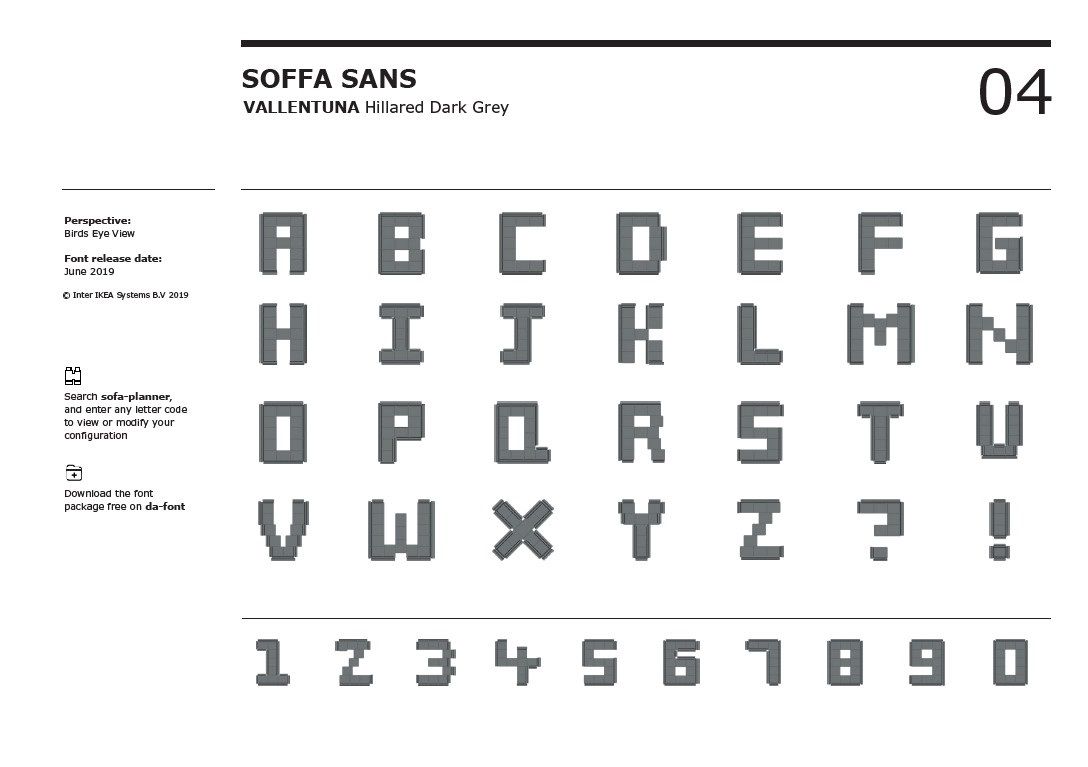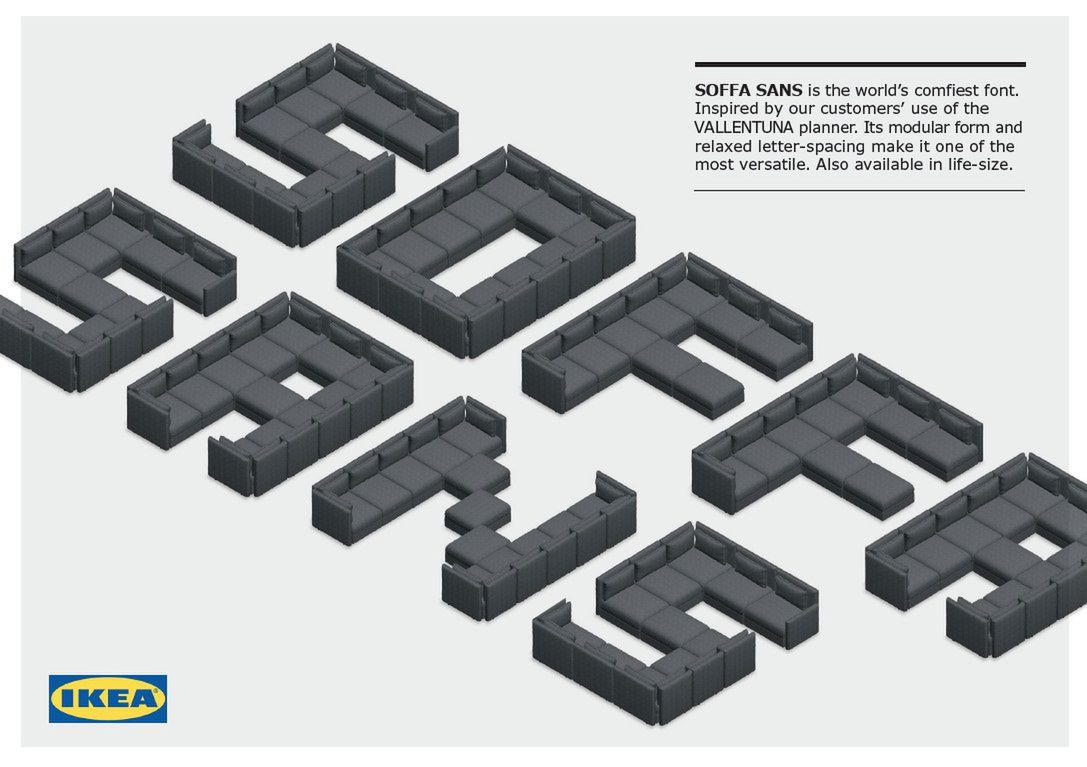
IKEA Soffa Sans. Kto by pomyślał, że sofa może zainspirować do stworzenia czcionki
Nie śpią, bo przeglądają internetowe memy. Tak, parafrazując klasyk polskiego dziennikarstwa, można podsumować najnowszy ruch PR-owców sieci IKEA. Wychodząc naprzeciw internetowym śmieszkom, szwedzki producent mebli udostępnia czcionkę o wymownej nazwie Soffa Sans.
Soffa Sans to czcionka, która jest inspirowana elementami sofy modułowej Vallentuna. Wygląda tak, jakby przedstawić Vallentunę w rzucie izometrycznym lub z lotu ptaka.
Skąd taki pomysł? – zapytacie. Otóż jakoś w połowie bieżącego roku internet opanowała moda na robienie sobie żartów z kreatora IKEA, który pozwala w dowolny sposób skonfigurować i zamówić wspomnianą sofę. Kiedy internauci spostrzegli, że narzędzie nie ma żadnych ograniczeń, zaczęli tworzyć i udostępniać iście zwariowane konfiguracje.
Szwedzi najwyraźniej podpatrzyli trend. Owocem tego jest właśnie czcionka Soffa Sans, stworzona we współpracy z brytyjską agencją reklamową Proximity London.
Jak wylicza "The Drum", gdyby ktoś zechciał zaaranżować Soffę Sans z produktów z oferty IKEA, musiałby zakupić dokładnie 1434 elementy. Kosztowałoby to około 134,5 tys. dol., a więc ponad pół miliona złotych. Zabawa czcionką natomiast jest całkowicie darmowa.